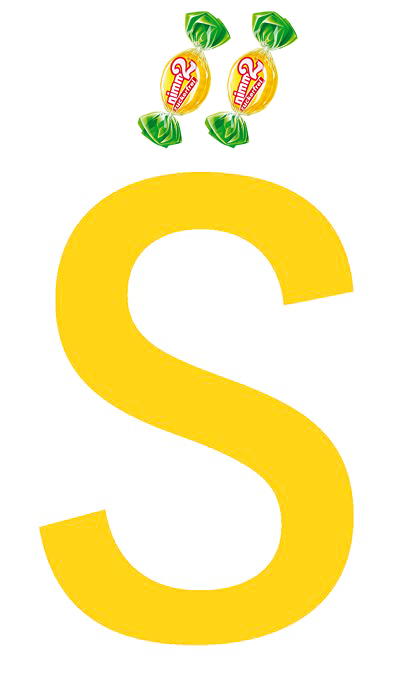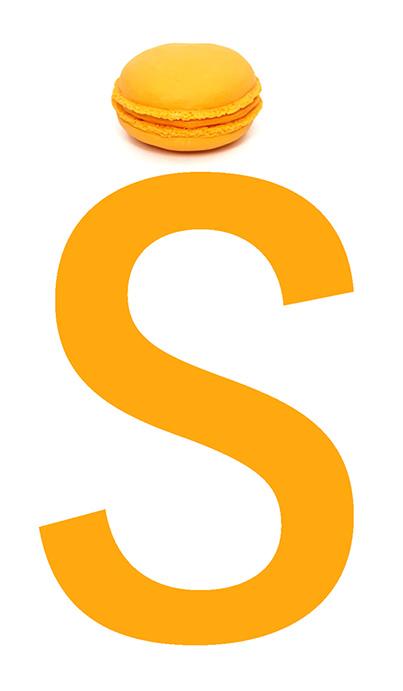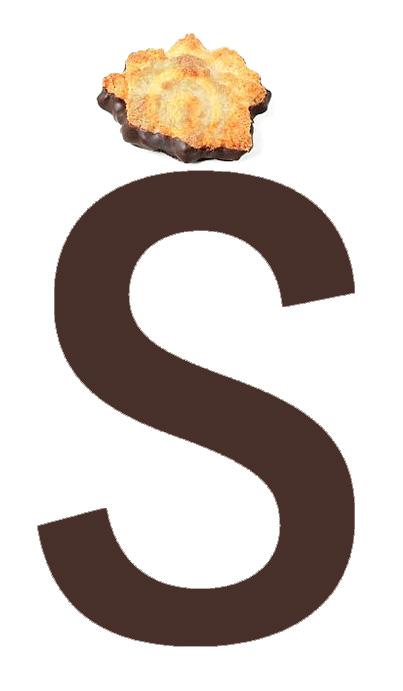
Nun ja, die Kleinbuchstaben sind ja dermaßen blöd auf die Stempel angeordnet, dass das nur zur Verwechslungen führen kann. Der »Gewinn« an Schriftgrösse, oder das »sauber füllen der Fläche« wird völlig wett gemacht von der unklare Handhabung von Ober- und Unterlängen. Da hat wohl jemand mit den Versalien angefangen und erst bei dem Kleinbuchstaben gemerkt, dass es sowas lästiges wie Ober- und Unterlängen gibt. Und war sich dann zu schade den eigenen Anfangsfehler zu beseitigen. Jetzt müssen wir mir den blöden Folgefehler leben. Tragischerweise müsste jemand das I und J der Futura mit Serifen und das q mit einem doofen Haken versehen. Anstatt eine andere Schrift zu nehmen oder einfach die Finger davon zu lassen, hat hier jemand gemeint es besser zu wissen als Paul Renner. Schade, schade!
Ich hätte allerdings schon ein Problem damit wenn das große ß nicht bloß eine Kann-Bestimmung bleibt aber zu Regel werden würde. Dann müsste ich für meine Schriften ein großes ß entwerfen. Ein furchtbarer Gedanke.
Wer sich fragt, ob es wahrscheinlicher ist, daß das große Eszett einen Platz auf der Handy-Tastatur bekommt oder daß es ganz, auch in seiner kleinen Erscheinung, von der Neuerungs- und Vereinfachungssucht ausgemerzt wird, muß sich darum keine Sorgen machen.
Bei allen bisherigen Varianten des Groß-ß finde ich keine Einzige die mich ästhetisch gesehen überzeugt. Alles zu »gewerkelt«, zu gebrochen und zu komplex in Vergleich zu den anderen lateinischen Großbuchstaben. Deswegen wird aus rein formaler Sicht keins wirklich dazu gehören. Mein Vorschlag: Schreibe das S mit einem Makron drüber. Die Lösung hat sich für allerhand Doppeltes über Jahhunderte bewährt.
Auch nicht so überzeugend ... also, ästhetisch. Aber ansonsten lecker.
Aus einer subjektiven Sichtweise schließt du das ein Versal-ß nicht dazugehören wird. Für dich nicht dazugehören wird oder allgemein niemals nicht? Für mich persönlich gehört es dazu, sowohl aus theoretischer als auch ästhetischer Sicht. Es gibt gelungene und weniger gelungene. So wie es gelungene und weniger gelungen Schriften gibt.
Ich habe mich anfangs mit dem Versal-ß schwer getan, natürlich sticht es hervor, aber häufig doch nur deshalb weil es nicht von kleinauf in unser Hirn eingebrannt hat.
In den nicht allzu häufigen Fällen in denen ich das Versal-ß anwenden konnte habe ich nicht speziell darauf hingewiesen, nur wenige sind wirklich darüber gestolpert, die Fälle wo es auffiel haben bisher durchweg positiv reagiert. Das ist nicht repräsentativ aber schön.
Auch wenn die Befürworter sich neuerdings ein theoretisches Konstrukt herbeiziehen können, was in deren Augen das Groß-ß rechtfertigt, heißt das noch nicht, dass damit das Problem aus ästhetischer Sicht gelöst ist.
Ich denke, wir brauchen eher weniger Zeichen als mehr. Schau doch mal wieviel Müll es bereits jetzt in Unicode gibt und wie eifrig die »Slot-Filler« auch die Zeichen basteln die kein Mensch mehr braucht. Die Glyphen-Palette sieht entsprechend aus …
Schriften und Zeichen sollen uns bei der Kommunikation helfen und diese nicht unnötig verkomplizieren.
Genau das macht das ẞ aus meiner Sicht auch. Der Umkehrschluss wäre dann wie die Schweiz ganz auf das ß/ẞ zu verzichten.
Das wäre mir ehrlich gesagt lieber!
Und ich denke, dass die Kann-Bestimmung für das Groß-ß sowieso dazu führen wird, dass es im Versalsatz demnächst nur so von Klein-ß wimmeln wird, dass uns dabei Übel wird. Alsob wir noch nicht genug Probleme haben.
Ok, dann war dein Vorschlag mit dem Makron Spaß, den hatte ich nicht verstanden :-)
Und bei Ŝ, Ş, Š etc. ist die Neigung nicht gering, es SCH auszusprechen.
Dafür gibt es die „kombinierenden diakritischen Zeichen.“ Die kann man hübsch bis zur Unleserlichkeit verteilen, um solche Buchstaben zu schreiben:  S̸̶͇͊͌⃠⃘⃙ͯ͛
Ja, kenn ich. Aber ist ja nun alles andere als eine Vereinfachung/Erleichterung/Hilfe :oops: